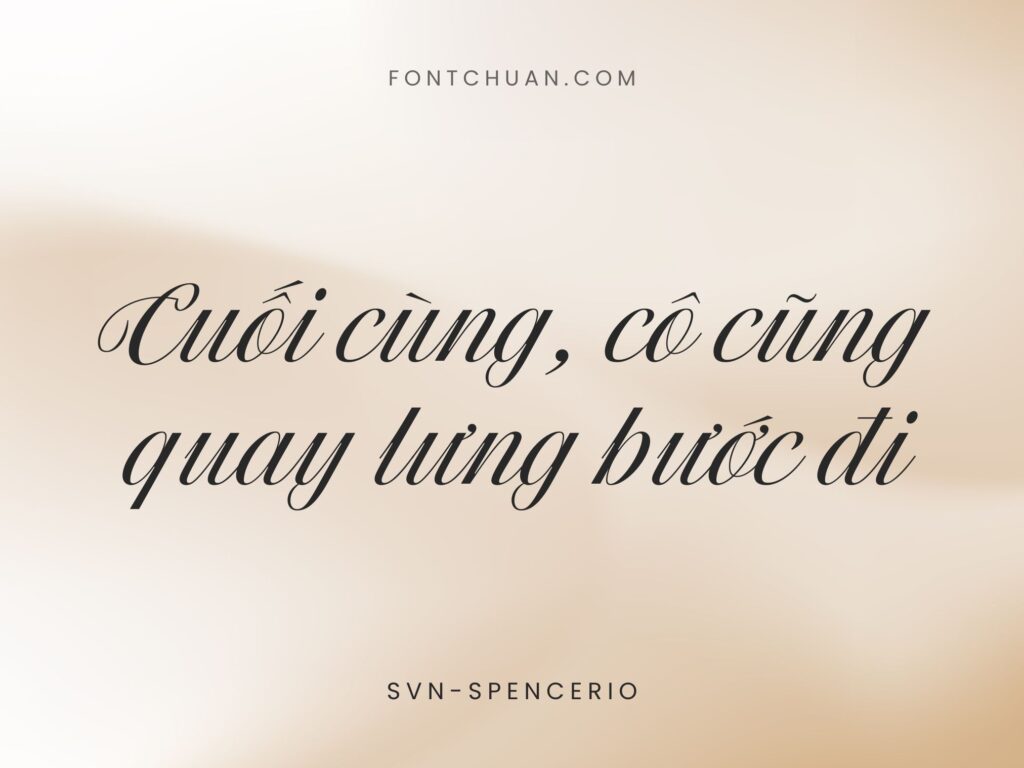
Font SVN Spencerio Việt Hóa
Tác giả Font: Jérémie Hornus
Font SVN Spencerio là phiên bản Việt hóa của kiểu chữ Spencerio, được thực hiện bởi STYLEno.1 Fonts. Spencerio được thiết kế bởi Jérémie Hornus, lấy cảm hứng từ thư pháp Spencerian truyền thống với các nét chữ nghiêng được viết bằng bút nhọn. Font này bao gồm 673 glyphs, hỗ trợ ligatures và các ký tự thay thế cho chữ cái đầu và cuối, giúp việc thiết kế chữ lồng trở nên dễ dàng. Spencerio là lựa chọn lý tưởng cho các ứng dụng yêu cầu chữ viết trang trọng như thiệp mời, bằng cấp hoặc thiệp cưới.
SVN Spencerio phù hợp cho các dự án thiết kế yêu cầu sự thanh lịch và trang trọng, như thiệp mời, logo, tiêu đề và các ấn phẩm truyền thông. Các ngành nghề như thiệp cưới, giáo dục và bất động sản có thể tận dụng font này để tạo điểm nhấn trong thiết kế. Ngoài ra, font cũng thích hợp cho các sự kiện như Tết, Valentine, Sinh nhật và các lễ hội khác.